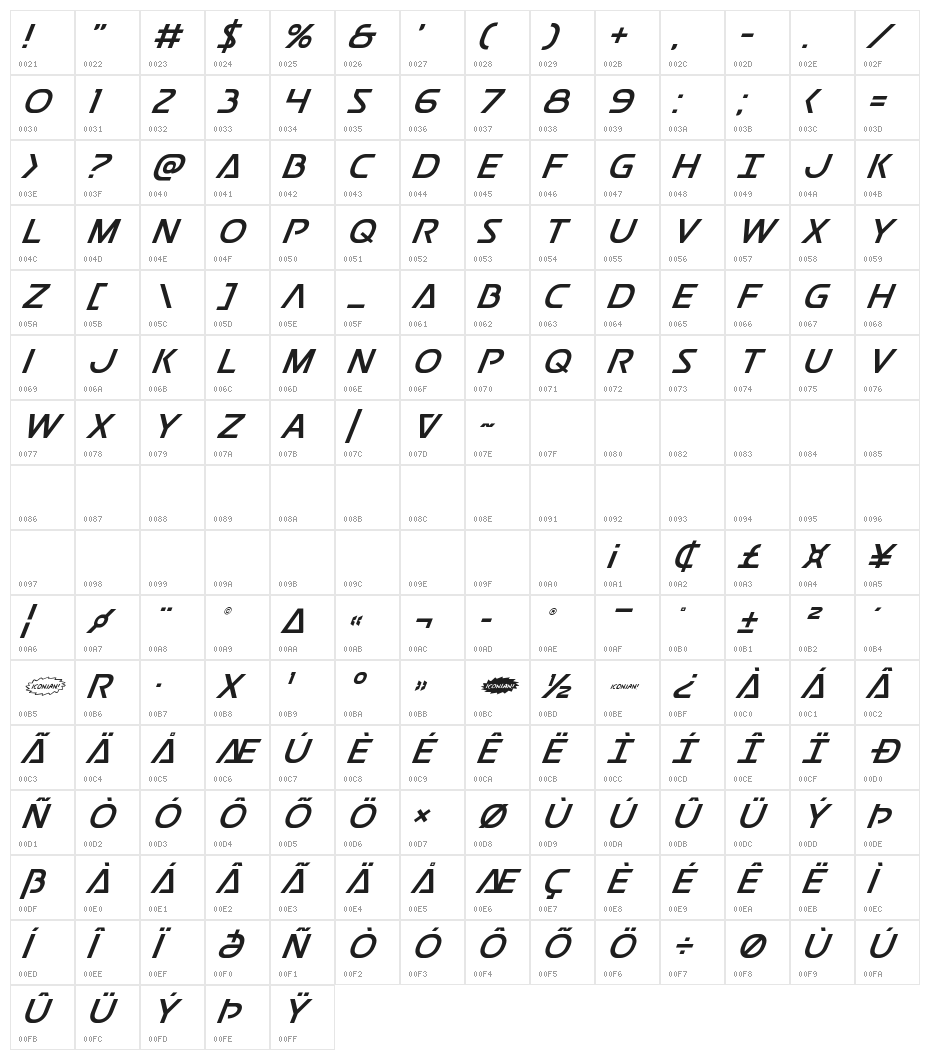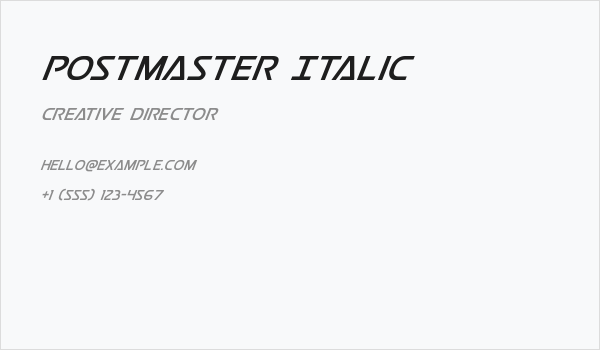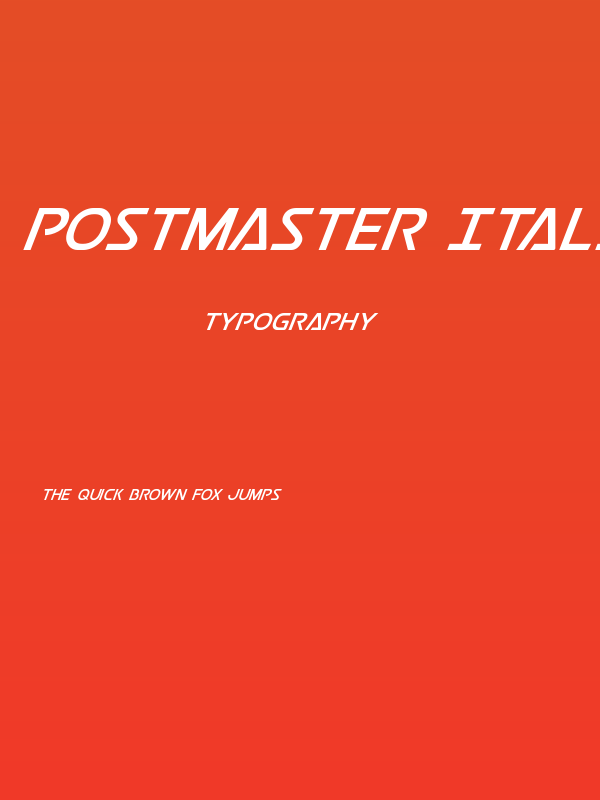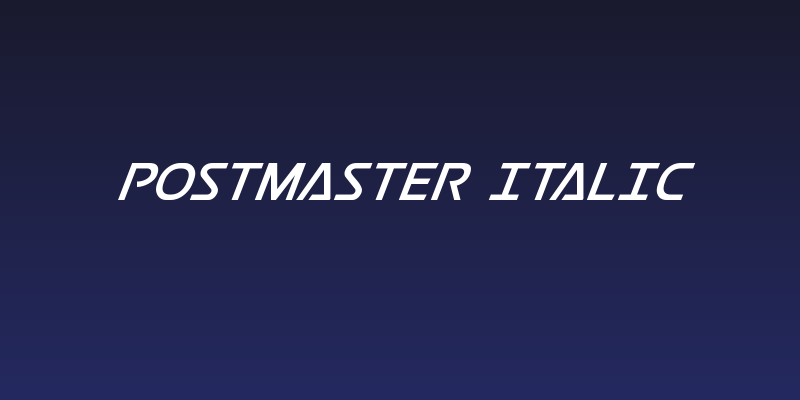
Postmaster Italic Font
| Nome | Postmaster Italic |
| Caso d'uso | Headlines, Logos, Branding |
| Progetti proposti | Ideal for branding, advertising, and editorial design projects that require a modern and dynamic touch. |